השאלון עם דולפין חיט
הכירו את דולפין חיט, מעצבת בת 25, בוגרת תואר בתקשורת חזותית בשנקר. דולפין גדלה בתל־אביב, שם היא גם חיה ופועלת כיום. את דרכה החלה בבתי ספר לאמנות, כשבמקור נמשכה לציור ולאיור, אך במהלך הלימודים גילתה את עולם הטיפוגרפיה והתאהבה בו. לדבריה, היא נמשכת בעבודתה לצבע, קומפוזיציה ולניסויים שמאתגרים את גבולות השפה החזותית. "הדבר שאני הכי אוהבת בעיצוב," היא מספרת, "נובע מהמשיכה שלי לאסתטיקה על כל הצורות והגוונים שלה, ומהיכולת לארגן את המציאות כך שתענה על צרכים ויזואליים ותהפוך מדויקת ונכונה יותר." כשאינה עובדת, דולפין בעיקר צורכת ואוספת תוכן – ממוזיקה ועד סרטים וסדרות, תוך חיפוש מתמיד אחר רעיונות ויזואליים חדשים.
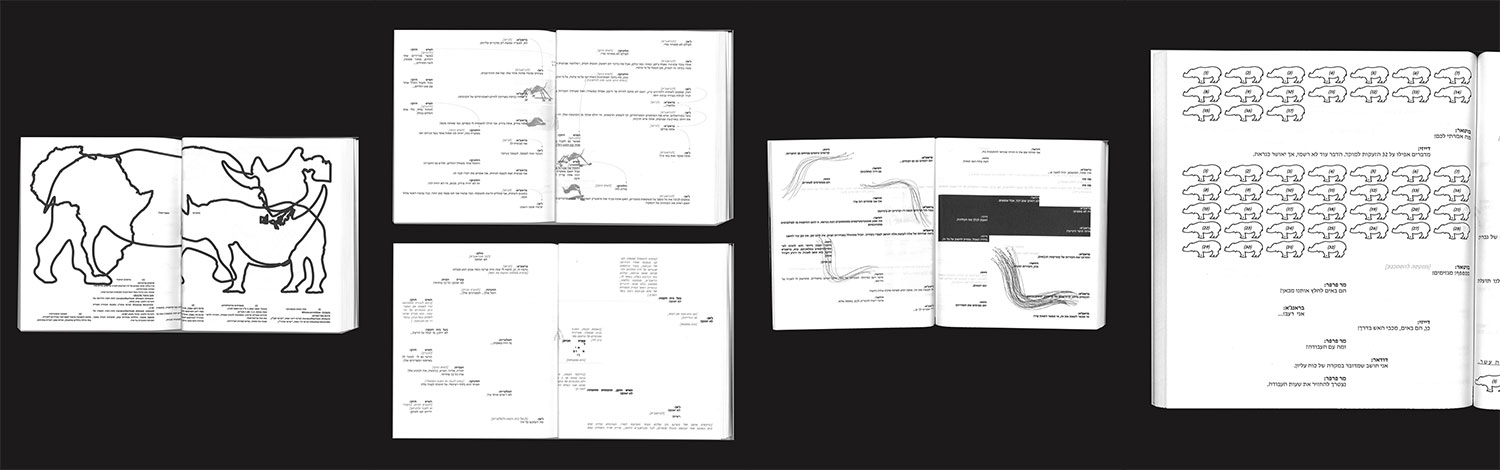
הפרויקט ״קרנפים״ של דולפין חיט הוא ספר שהוא פרשנות גרפית למחזהו של אז׳ן יונסקו, שבו הוראות הבימוי מקבלות צורה ויזואלית חדשה. העבודה נולדה מתוך בריף שהתמקד בחוקים ופקודות, כמעט כמו כתיבת קוד. דולפין לקחה את המחזה, תמללה אותו, והגדירה כל הוראת בימוי כ״פקודה״ שממנה פיתחה את השפה הגרפית של הספר. התוצאה היא ספר שהוא גם במה, וגם מערכת חוקים שמתרגמת תיאטרון לעיצוב גרפי. הפרויקט נעשה במסגרת הקורס ״שם קוד: ספר״, בהנחיית דקל בוברוב.
תמיד ידעתי שאני רוצה להתעסק בעיצוב, נראה לי שלא באמת הבנתי מה זה אומר. הגעתי מעולמות של אמנות ויצירה, אבל אפשר להאשים את אמא שלי שהייתה מעצבת בעברה, ואת זה שבתור ילדה ראיתי יותר מדי Mad Man.
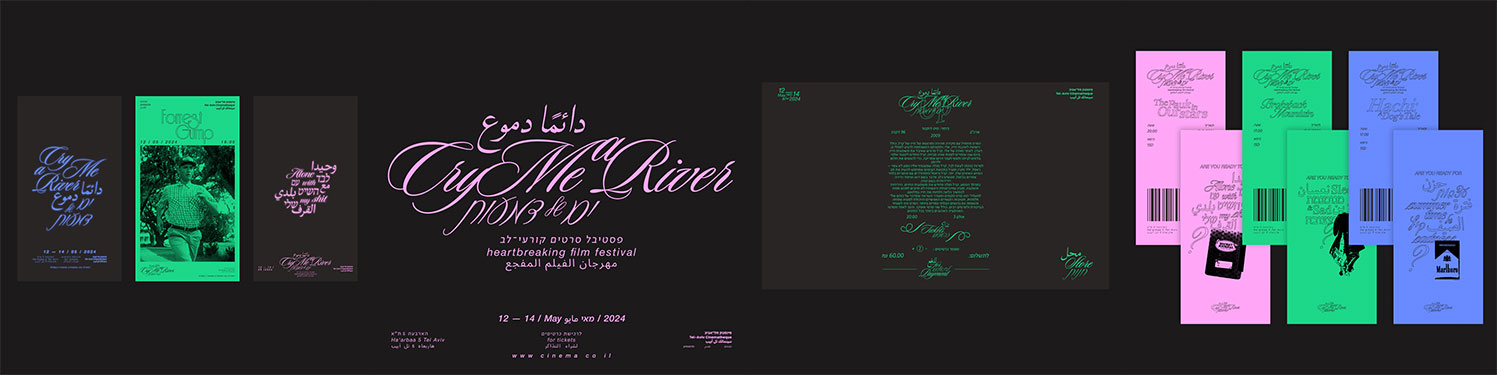
הפרויקט ״ים של דמעות״ הוא פסטיבל קולנוע דמיוני שעיצבה דולפין חיט, המוקדש כולו לסרטים שוברי־לב – כאלה שמבטיחים לגרום לצופים לבכות. עיצוב הפסטיבל שואב השראה משני עולמות: עולם הקולנוע הקלאסי עם הרומנטיקה של הקרדיטים והטייטלים, לצד אסתטיקת ה־Sad Girl שהתפתחה סביב 2014 וחגגה את המלנכוליה. המפגש בין שני העולמות יוצר שפה אקלקטית שמשלבת רומנטיקה, אלמנטים קלאסיים וקיטש אהוב – יחד הם בונים חוויה ויזואלית עשירה ומלאת רגש. הפרויקט נעשה במסגרת קורס עיצוב מרובה פלטפורמות, בהנחיית קובי פרנקו.
באיזה פונט את רוצה שיכתבו על המצבה שלך?
פרנק־ריהל כמובן.